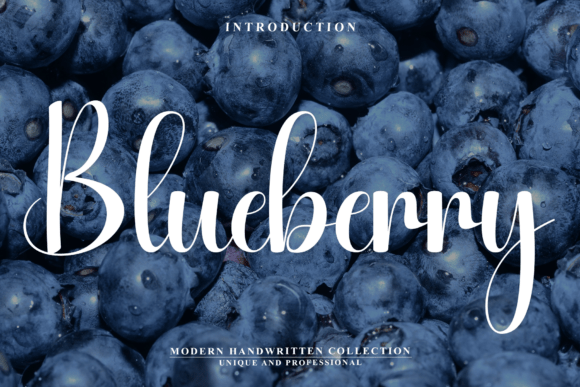
Blueberry
Encontrar los elementos de diseño adecuados puede ser un desafío, pero Blueberry ofrece una colección excepcional que eleva tu trabajo al instante.
Ya sea que estés creando productos POD (impresión bajo demanda), invitaciones de boda o gráficos para redes sociales, Blueberry es una opción ideal.